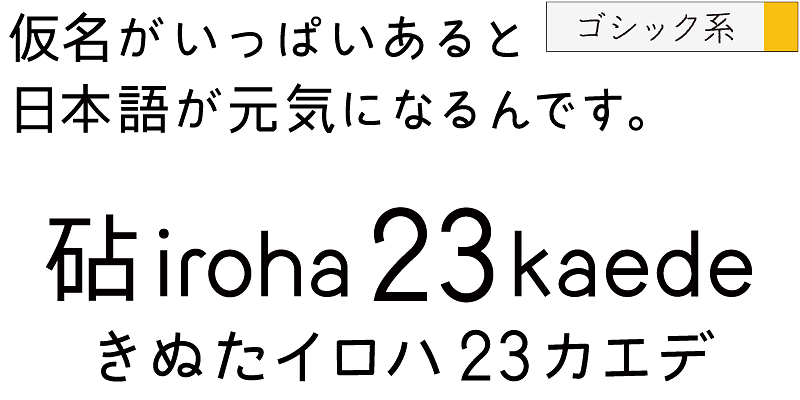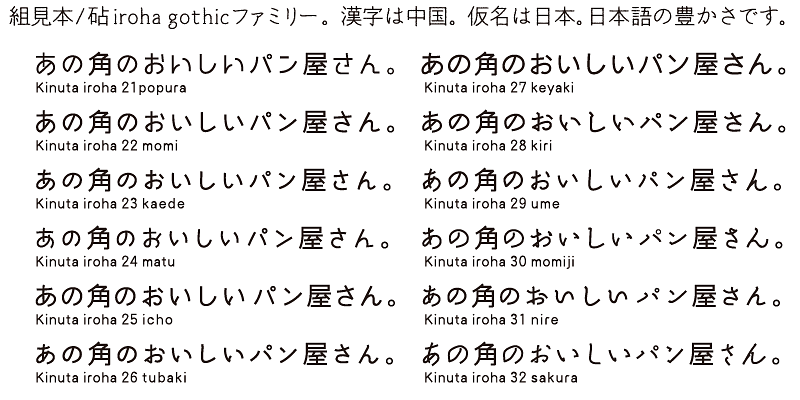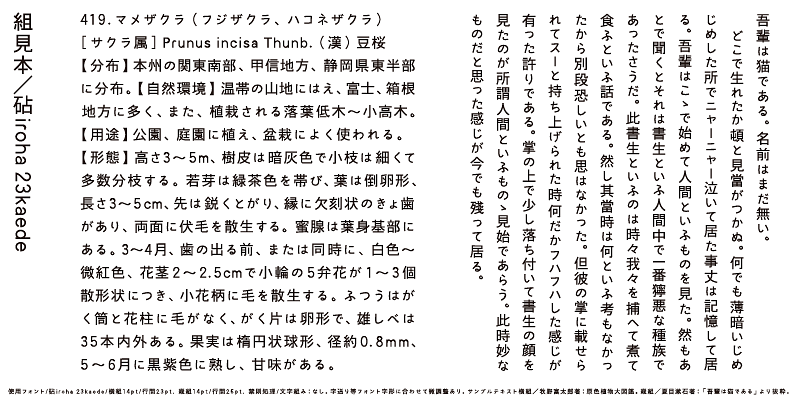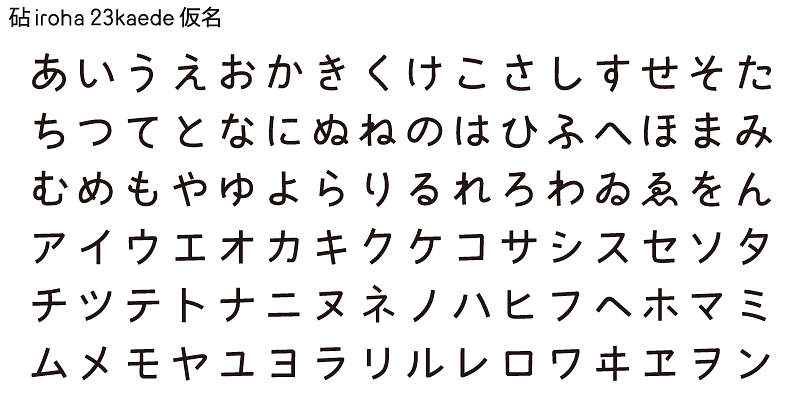
Los caracteres kana de Iroha 23kaede son mucho más pequeños que los caracteres kanji, lo que acentúa la dulzura del diseño.
Todas las variantes de Iroha comparten los mismos caracteres ideográficos (kanji). Los caracteres kanji de Iroha están diseñados con trazos lineales y estructuras simples. Hay 12 variantes de kana.
Una característica del japonés es que tiene caracteres silábicos llamados kana. Los caracteres kana se inventaron para representar sonidos en japonés y traducir textos importados de China. Los caracteres kana son necesarios para crear palabras y expresiones japonesas a partir de caracteres ideográficos kanji, que son caracteres chinos. Si bien puede haber ambigüedades, estas palabras y expresiones exhiben la cercanía y amabilidad de las personas que viven en la pequeña y densamente poblada tierra de Japón.
Kinuta Font Factory cree que los caracteres kana son el origen de las palabras escritas en japonés, y que mejorar los caracteres kana hará que el texto japonés sea más atractivo. En promedio, el 60 % del texto japonés se compone de caracteres kana; cambiar la forma de estos caracteres cambia la apariencia visual del texto. Las posibilidades de expresión tipográfica utilizando caracteres kana sencillos, dinámicos y curvilíneos son enormes, y la riqueza del texto japonés depende de ellos en gran medida. Esta es la razón por la que Kinuta Font Factory ofrece muchas variaciones de tipos de letra kana.